Шрифт в Apple Watch подозрительно похож на шрифт из Android
The Verge отметил сходство шрифта, использованного Apple в представленных вчера смарт-часах Apple Watch со шрифтом Google Roboto, который появился в Android 4.0 почти три года назад. Это простой, легкий рубленый шрифт, который хорошо читается на экранах с небольшим разрешением.
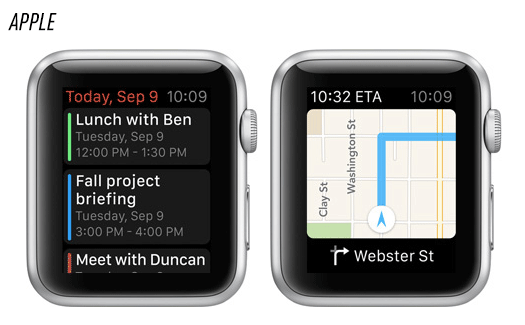
Хотя Apple недавно применила тонкий шрифт без засечек Helvetica Neue в iOS и OS X Yosemite, в интерфейсе смарт-часов она почему-то отдала предпочтение не ему. Вряд ли Google будет выставлять претензии Apple, ведь в Android L и Android Wear используется уже другая версия шрифта Roboto, еще более совершенная, которая одинаково хорошо подходит экранам и с низким, и с очень высоким разрешением.